השאלון עם הדר לוזון
הכירו את הדר לוזון, ילידת 1995, בוגרת המחלקה לתקשורת חזותית בשנקר (2023). הדר עוסקת במיתוג, ולפעמים משלבת בעבודתה גם איור ומושן גרפיקס. היא נולדה ביישוב מתן וכיום חיה בתל־אביב. מה שהדר אוהבת בעיצוב זה שהוא מקור להשראה אינסופית, מבחינתה, "כשמיתוג פוגע בול, הוא לא רק נראה טוב – הוא מרגש, מדבר, נשאר. וזה הקסם". גם מחוץ לשעות העבודה, הדר ממשיכה ליצור – אם זה בפרויקטים אישיים, עבודות לחברים, או ניסויים במדפסת התלת־ממד הביתית שלה. בנוסף, היא חובבת קפה נלהבת, ותמיד נמצאת בציד אחר בתי קפה יפים וטובים בעיר.
היי הדר, מה שלומך? איפה אנחנו תופסים אותך השבוע?
היי היי, בדיוק חוזרת משבועיים ברצלונה, אחרי פסטיבל OFFF שהיה מפוצץ השראה ואנשים טובים.
איזה כיף! איפה את עובדת עכשיו?
אני פרילנסרית, ועובדת בשנה וחצי האחרונות על פרויקטים ומיתוגים עם סטודיו under.
את מעדיפה לעבוד לבד או בצוות?
אני מעדיפה לרוב לעבוד בצוות, ומאמינה שחשיבה משותפת מפרה, מלמדת ומקדמת את התהליך היצירתי. גם כשאני עובדת לבד, חשוב לי שתהיה סביבי נוכחות זמינה של חבר או חברה שאפשר להתייעץ איתם, לשתף ולהתפתח יחד. בעיניי, עיצוב הוא תהליך שצומח ונעשה טוב יותר כשיש אנשים סביבך שחושבים ויוצרים יחד – וזה גם הרבה יותר כיף.
על איזה פרויקט מעניין עבדת לאחרונה?
אחד הפרויקטים המעניינים שעבדתי עליהם לאחרונה היה בשיתוף עם סטודיו under, על מיתוג לעיר עתלית. הפרויקט התחיל מתוך חיבור אישי – החבר׳ה מהסטודיו גרים בעתלית, והקשר העמוק שלהם למקום הורגש כבר מההתחלה. במסגרת תהליך המיתוג ערכנו מחקר עמוק על ההיסטוריה של היישוב והתפתחות הלוגו לאורך השנים. בהמשך, נסעתי לבקר בסטודיו בעתלית, לסייר יחד ביישוב, להכיר את האנשים ולחוות מקרוב את האווירה והייחודיות של המקום. השילוב בין המחקר, ההיכרות האישית והחוויה בשטח הפך את התהליך לעמוק, מדויק ומעורר השראה.
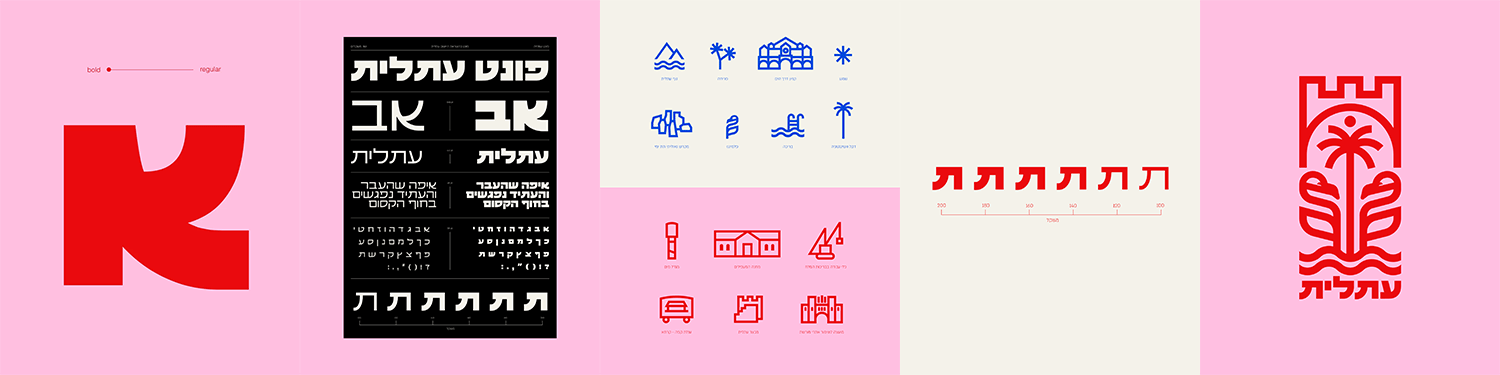
פונט "עתלית" נולד במסגרת תהליך מיתוג מחדש ליישוב עתלית, שביצעה הדר לוזון כחלק מעבודתה בסטודיו under.design. הפרויקט החל במחקר יסודי של הלוגו המקורי שעיצב דרור בן־דב, ובחן את מקורותיו החזותיים ואת הקשרו התרבותי־מקומי. מתוך המחקר הזה צמחה שפה טיפוגרפית חדשה, שעושה כבוד להיסטוריה תוך התבוננות אל העתיד. הפונט משלב עגלגלות רכה, בהשראת נופי הסביבה – הים, ההרים ובריכות המלח – עם רמזים צורניים לכתב ביזנטי מקומי עתיק. הדר מספרת: "רציתי שהאותיות יספרו את הסיפור של המקום – שורשיות, קהילתיות וחדשנות." כך נולד פונט שהוא לא רק כלי תקשורת, אלא גם סמל זהות מקומית.
מה הדבר הכי טוב שקרה לך השנה?
הדבר הכי טוב שקרה לי השנה היה למצוא את סטודיו under ולהתחיל לעבוד איתם. הבנתי שגם אחרי הלימודים בשנקר, אפשר להמשיך ליהנות מעיצוב וליצור דברים מיוחדים גם ב"חיים האמיתיים". זה הרגיש כמו פארק שעשועים למעצבים – להתנסות בפלטפורמות מגוונות, לחקור, לשחק עם תוכנות חדשות, וליהנות באמת מהיצירה. זה מקום שמאפשר לחשוב יצירתי, לזרוק רעיונות בלי פחד, לדייק שפה חזותית, להתמודד עם לקוחות, וגם ללמוד איך להיות יותר עצמאית.
מה גורם לך להתרגש ולרצות לעצב וליצור?
ההשראה שלי מגיעה מהסביבה, ממש מכל דבר שנמצא סביבי. זה יכול להיות שלט ברחוב, עיצוב של חנות, פוסטר אקראי, בתים של אנשים או אפילו שקופית מתוך הרצאה וכמובן מהאינסטגרם. כשאני נתקלת בעיצוב שתופס לי את העין, כזה שאני עוצרת לצלם או פשוט חושבת עליו אחר כך, זה מיד מדליק בי משהו. זה גורם לי לרצות לחזור הביתה, לשבת מול המחשב וליצור. כל מה שמסקרן, נוגע או מפתיע אותי – הופך לדלק ליצירה.
מה את עושה בשביל הכיף?
אני ממשיכה ליצור ולעצב גם בשעות הפנאי – לעצמי, לחברים, או פשוט כדי להתנסות וללמוד. מעבר לזה, אני אוהבת לשוטט ולגלות בתי קפה חדשים בתל־אביב, ולפעמים גם מחוץ לעיר.
יצא לך לטייל בחו״ל?
בטח! יצא לי לטייל בחו״ל, בעיקר טיולים קצרים ברחבי אירופה. אני מאוד אוהבת להסתובב במקומות חדשים ולספוג השראה מהסביבה – בין אם זה בעיצוב רחוב, טיפוגרפיה מקומית, חלונות ראווה או אסתטיקה עירונית אחרת. כל מקום מביא איתו שפה חזותית קצת אחרת, וזה תמיד מרתק אותי.
מה משך אותך לתחום?
מאז שאני זוכרת את עצמי הייתי מוקפת ביצירה. סבא שלי, שהיה אדריכל, לימד אותי כבר בגיל צעיר לעבוד עם תוכנות שרטוט. אמא שלי הייתה כותבת לי כותרות לברכות בכתב־יד יפהפה, ודודים שלי מוזיקאים – כך שהיצירה הייתה חלק בלתי נפרד מהסביבה שלי. גם בתנועת הנוער תמיד הייתי זו שמאיירת חולצות וכותבת שלטים. כשראיתי כמה כוח יש לעיצוב חזותי להעביר תחושה, מסר או סיפור – ידעתי שזה התחום שאני רוצה לעסוק בו. את התואר בתקשורת חזותית גיליתי דרך חברה, ומיד נשאבתי לעולם האינסופי הזה.
לאן ניסית להתקבל ללימודים ולאן התקבלת?
ניסיתי להתקבל ל־HIT, בצלאל ושנקר. התקבלתי ל־HIT ולשנקר, אבל היה לי ברור שאלך לשנקר – זה היה החלום שלי מהרגע שהתחלתי לחשוב על לימודי תקשורת חזותית.
איזו מרצה השפיע/ה עלייך במיוחד?
המרצה שהשפיע עליי במיוחד הוא עידן עם־שלם. למדתי איתו כמה קורסים – טיפוגרפיה, מיתוג ועוד. מהר מאוד הבנתי כמה הוא משמעותי בשבילי בתהליך הלמידה. הוא נתן ביטחון להביא כל סקיצה לשיעור, גם אם היא לא מושלמת, ולמדתי ממנו לשחרר רעיונות יפים כשצריך, ולהישאר עם מה שנכון ומדויק. עידן עודד חשיבה יצירתית, לא טרנדית, והזכיר להשתמש בהשראות כהשראות בלבד. הוא גם גרם לי לחשוב רחב יותר – לא רק על הלוגו או השפה החזותית, אלא גם על המעטפת המיתוגית כולה: מרצ'נדייז, פריטי שיווק, ואיך מותגים חושבים כשהם מוציאים מוצר – מתוך הבנה שכל נכס מיתוגי הוא הזדמנות לחזק את הסיפור והזהות של המותג. הוא ידע להעצים ולכוון, והגביר בי את הרצון להשקיע, לדייק וללטש כל פרט עד הסוף.
במה היית עוסקת אם לא היית מעצבת?
אני מאמינה שעדיין הייתי עוסקת במשהו אחר שקשור ליצירה – אולי מעצבת תכשיטים. אני מאוד אוהבת לעבוד עם הידיים, ותמיד אהבתי את הקסם שתכשיטים יכולים לייצר. סבא שלי היה אדריכל ורצה שאמשיך את דרכו, כך שהיה לי ברור שמקומי תמיד יהיה בעולם האמנות.
יש לך המלצה מוזיקלית?
Star Lord’s Playlist. לפני שנה-שנתיים עשיתי בינג' על כל סרטי מארוול ומאז התמכרתי. הפלייליסט הזה נכנס בעקבות הסרטים – הוא משלב וייב מגניב, נוסטלגי ומרים, אבל לא בקטע מוגזם. בדיוק מה שצריך כשרוצים לעבוד בכיף.
קיצור מקלדת אהוב.
Cmd+Z, והלוואי שהיה אפשר לעשות את זה גם בחיים האמיתיים.
כתב/י בבקשה את המילה הבאה בכתב היד שלך: